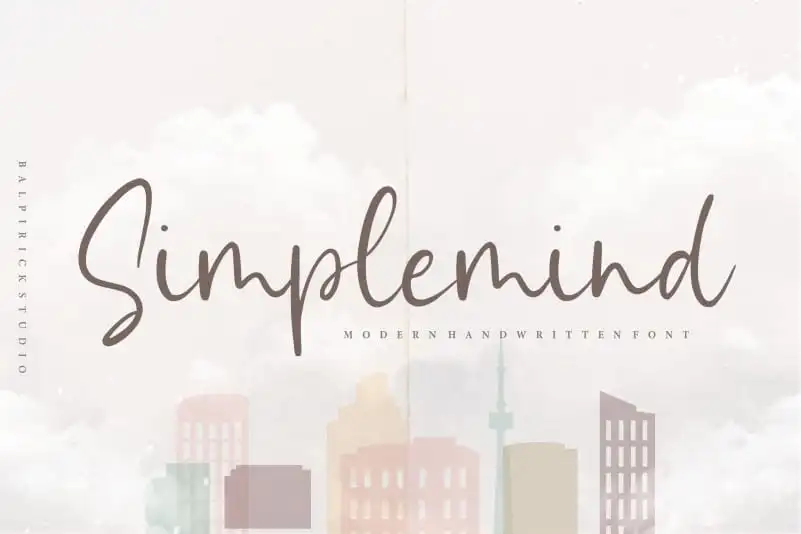
A fonte ‘Simplemind Modern Handwritten Font’ é perfeitamente adaptada para várias necessidades digitais no Brasil, onde a escrita criativa é valorizada. Suas linhas suaves e expressivas tornam-a ideal para aplicativos como embalagens de produtos, projetos de marca, revistas, mídia social, casamentos ou qualquer outro uso que exija uma escrita textual destacada em um fundo mais sólido. A estética moderna e minimalista dessa fonte, combinada com a personalidade expressiva dos traços manuscritos, permite criar designs vibrantes e únicos. Seja você criando uma campanha de marketing dinâmica ou apenas adicionando um toque especial à sua próxima publicação de casamento, esta fonte oferece opções para expressar ideias e sentimentos de forma única e profissional. Ela é perfeita não apenas por permitir que você destaque o texto acima do fundo com graciosidade e estilo, mas também porque suaviza qualquer informação técnica ou funcional em seu design. Portanto, ela pode ser usada para criar notificações engajantes no Instagram ou newsletters de loja, ou mesmo para personalizar as cartas de casamento num tom apropriado. Em resumo, esta fonte é uma escolha versátil e inspiradora para qualquer designer que procura dar um toque humano e emocional a suas criações digitais.